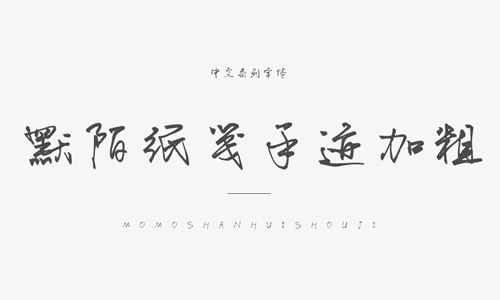
默陌紙箋手跡加粗字體是一款非常漂亮的手寫(xiě)字體,似硬筆書(shū)法又似毛筆書(shū)法,非常不錯(cuò),可以適合應(yīng)用于廣告設(shè)計(jì)、名片設(shè)計(jì)、包裝印刷、產(chǎn)品設(shè)計(jì)等應(yīng)用,歡迎有需要的朋友們前來(lái)下載使用。